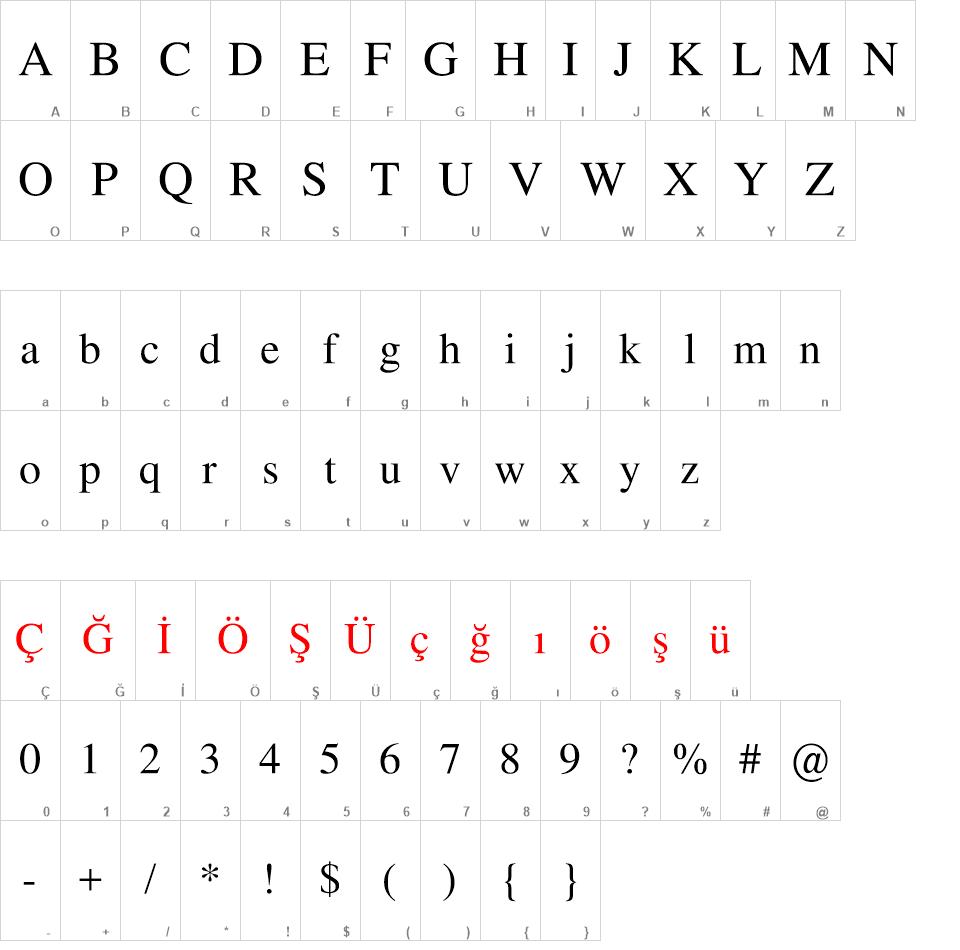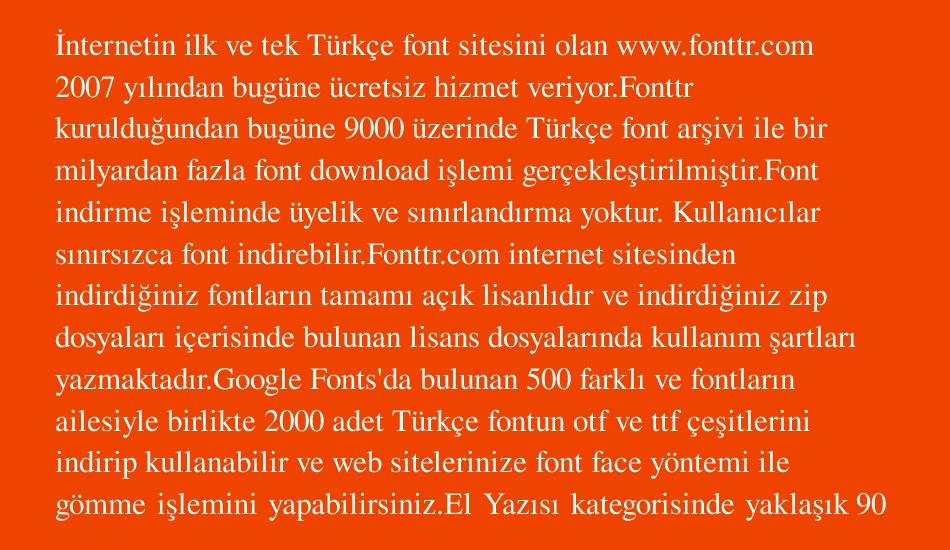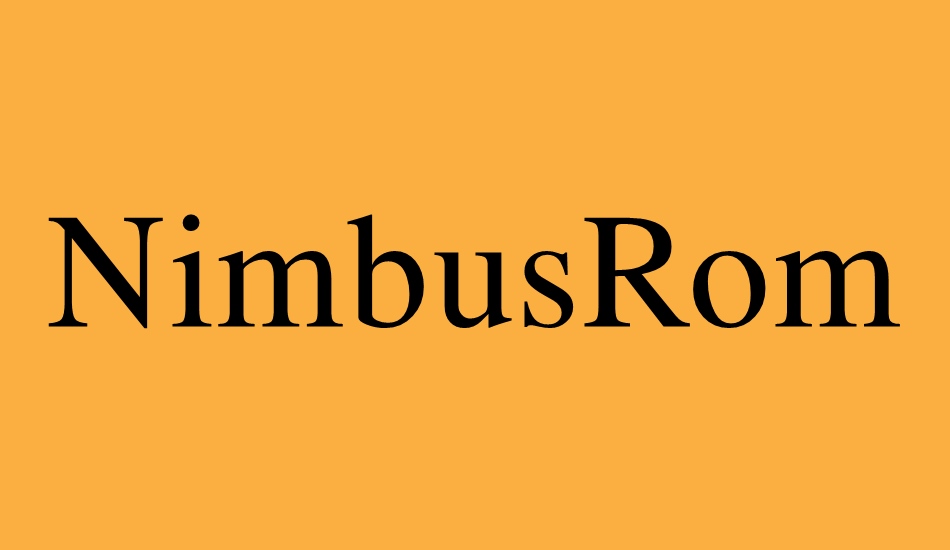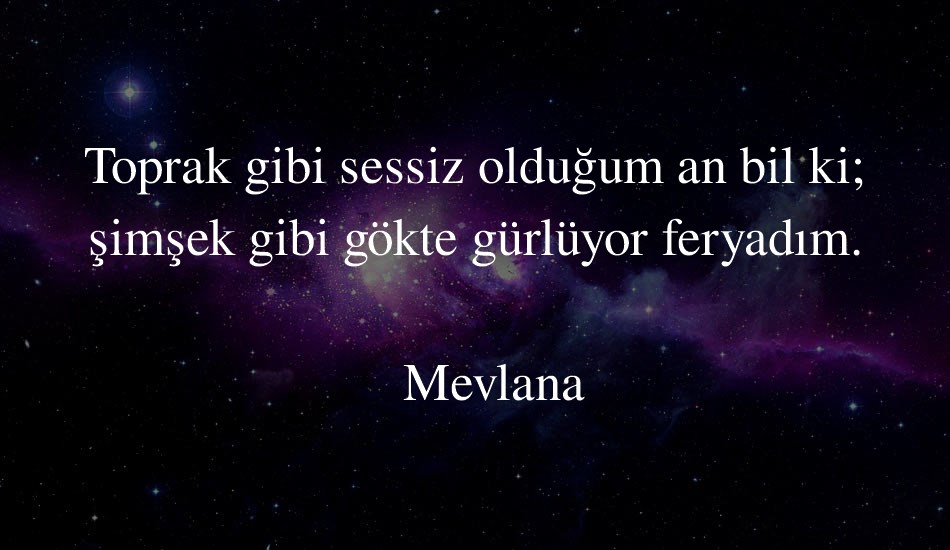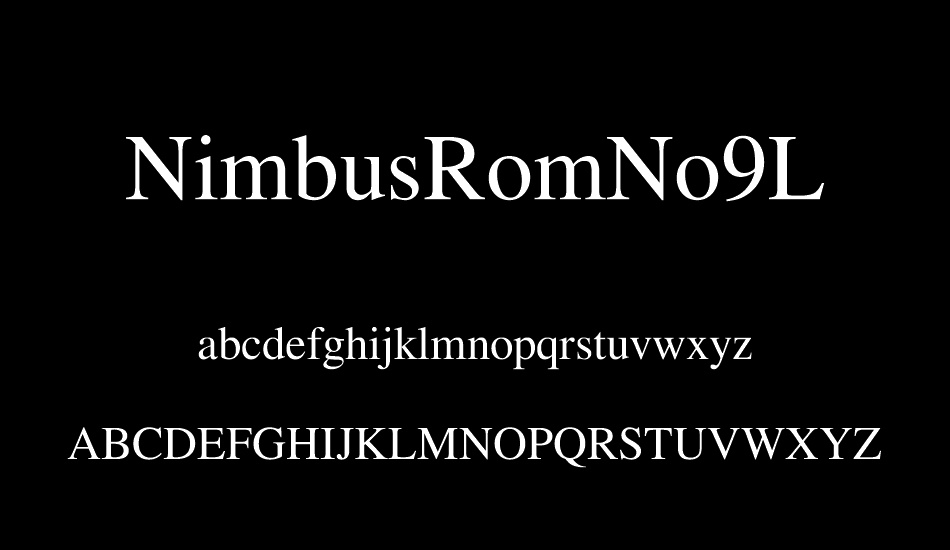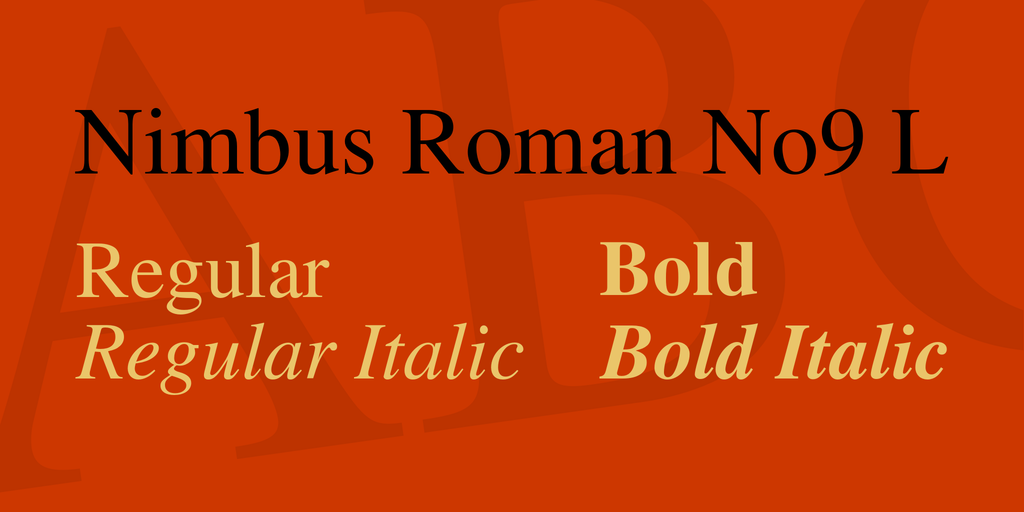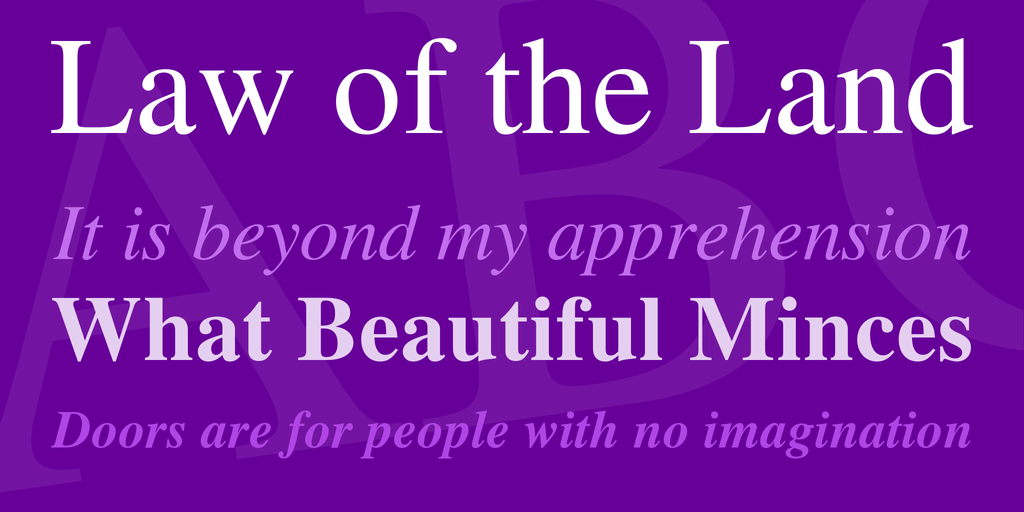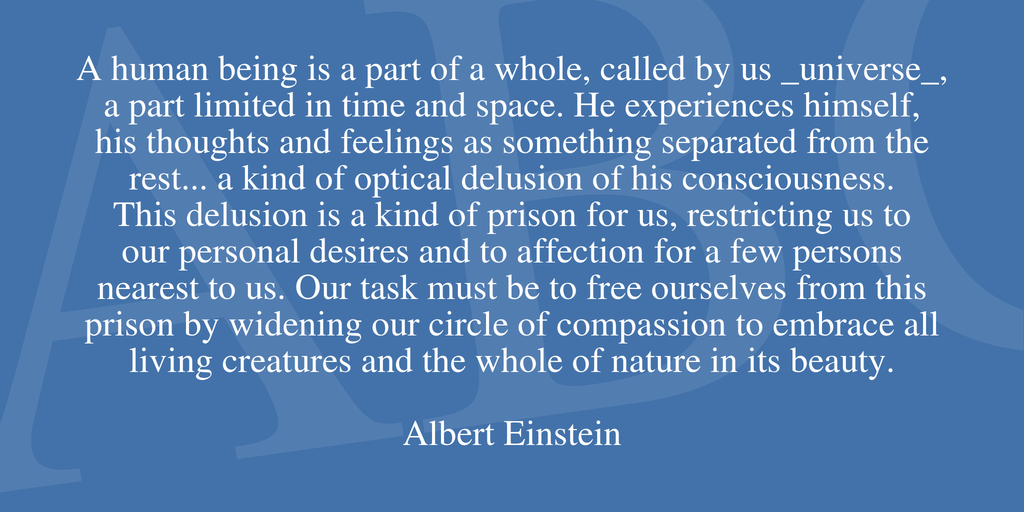
Wikipedia'dan: Nimbus Roman, URW Studio tarafından 1982'de oluşturulmuş bir serif yazı biçimidir.
Nimbus Roman No 9 L, URW Studio tarafından 1987'de oluşturulmuş ve sonunda 1996'da GPL ve AFPL (Ghostscript için Tip 1 yazı tipi olarak) ve 2009'da LPPL'de serbest bırakılan serif yazı biçimidir. Normal, Kalın, İtalik ve Koyu İtaliktir Ağırlıkları ve URW ++ tarafından sunulan serbestçe lisanslı fontlardan biridir.
Karakterler tam olarak aynı olmasa da, Nimbus Roman No 9 L, Times ve Times New Roman ile neredeyse aynı ölçütlere sahiptir. Ghostscript yazı tiplerinden biridir, 35 temel PostScript fontuna (Times dahil) ücretsiz bir alternatiftir.
Birçok Linux dağıtımı standart bir yazıdadır. Bazı Linux dağıtımlarında OpenOffice.org Writer'da varsayılan yazı tipi olarak kullanılmıştır (ör. Ubuntu - 8.10 sürümüne; Ubuntu 9.04'ten beri varsayılan yazı tipi Kurtuluş Serif olarak değiştirilmiştir).